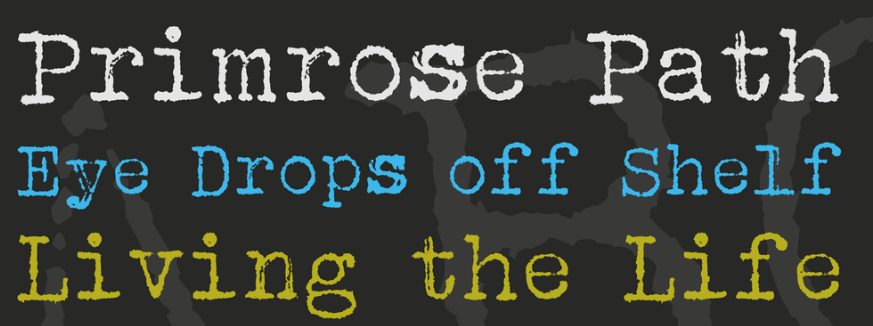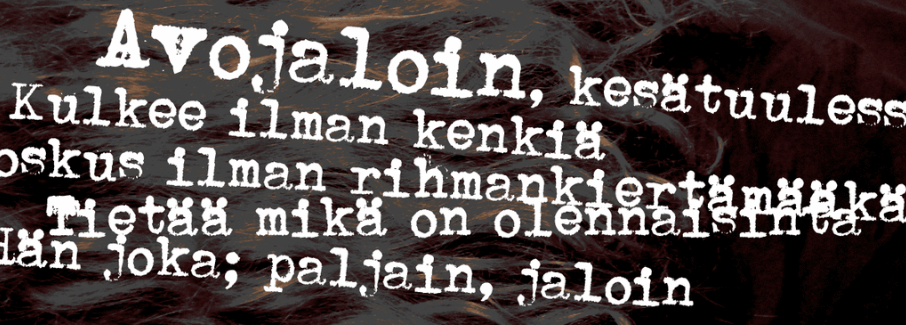
12 лучших шрифтов для пишущей машинки для классического стиля писателя
Опубликовано: 2018-10-27В наши дни кажется, что все соревнуются, чтобы создать самый современный дизайн. Тем не менее, есть что сказать о том, чтобы время от времени погружаться в ностальгию. В некоторых случаях классический шрифт пишущей машинки может быть идеальным элементом, чтобы добавить немного винтажного стиля в ваш дизайн.
В этой статье мы собираемся показать вам 12 наших любимых шрифтов для пишущей машинки. Пойдем винтаж!
12 лучших шрифтов для пишущей машинки для классического образа писателя
В этом обзоре мы сосредоточились на забавных шрифтах для пишущей машинки, которые легко читать. Таким образом, вы сможете использовать их как часть любого элемента вашего дизайна, хотя они особенно хорошо подходят для логотипов.
1. Пишущая машинка почтовых марок
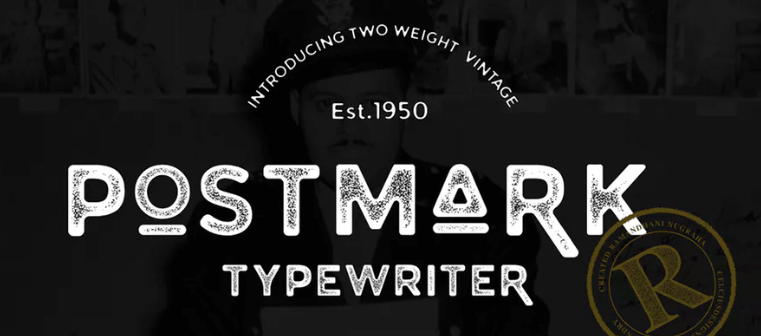
Для начала у нас есть Postmark Typewriter, прочный шрифт, который выглядит так, будто его выплюнули из самой старой пишущей машинки, которую вы можете найти. Этот шрифт без засечек имеет толстые линии (что облегчает чтение) и не будет выглядеть неуместным на современном сайте, несмотря на его наследие.
2. Семейство шрифтов Manson
Далее, семейство шрифтов Manson выглядит так, как будто оно появилось прямо на пишущей машинке 3018. Этот шрифт с засечками включает три разных веса, самый легкий из которых будет отлично смотреться на веб-сайтах, связанных с технологиями. Кроме того, по мере того, как шрифт становится толще, он становится более причудливым, что делает его универсальным вариантом.
3. Не мой тип
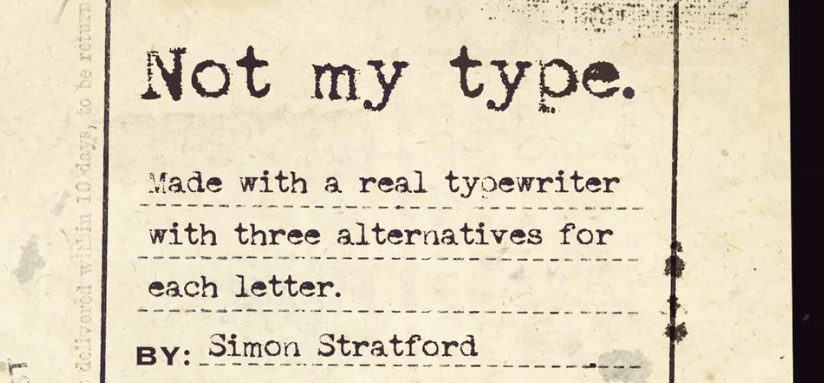
Not My Type - это шрифт, который вы ожидаете увидеть на старых открытках времен Второй мировой войны. У него выцветшие границы, и есть заметная разница между толщиной стеблей и штрихов. На практике это сочетание дает почти рукописный стиль, только более механический.
4. Заговор
Сторонники заговора часто бывают немного «чокнутыми», и этот шрифт прекрасно отражает их причудливость. Хотя похоже, что это написано на пишущей машинке, вы можете заметить, что буквы не идеально выровнены, что придает шрифту более беззаботный стиль. Мы бы не рекомендовали использовать его на бизнес-сайте, но он не будет выглядеть неуместным в блоге или портфолио.
5. Секретная пишущая машинка
Secret Typewriter - отличное название шрифта и идеальное описание стиля этого шрифта. Хотя этот шрифт очень легко читать, вы заметите, что большая часть его букв покрыта кистью, из-за чего он выглядит нечетким. Эти недостатки - идеальный способ добавить немного стиля к простому, элегантному шрифту, который отлично подходит для блогов.
6. Типы старых газет
Old Newspaper Types находится на грани между пишущей машинкой и готическим шрифтом. Его волнистые линии станут отличным дополнением, если вы хотите добавить немного причуды своему сайту. Однако из-за его уникального стиля мы рекомендуем использовать его только для заголовков, поскольку он плохо переносится на меньшие размеры.
7. Плохо штампованные
Если вы когда-нибудь хотели использовать шрифт, который выглядит как буквы из записки о выкупе, одобренной ТВ, Badly Stamped поможет вам. Это определенно не тот шрифт, который вы хотите использовать для контента или подзаголовков вашего сайта, но он является отличным вариантом для логотипов или для раздела заголовка.
8. Молотковые ключи.
Из всех шрифтов, которые мы видели до сих пор, Hammer Keys - это тот, который ближе всего передает стиль старой пишущей машинки. Стиль шрифта тонкий и почти хрупкий, что не делает его хорошим вариантом для мелкого текста. Однако, несмотря на это, Hammer Keys - это то, что вам нужно, если вы ищете почти точную копию стиля винтажной пишущей машинки.
9. Ремингтон Ривьера
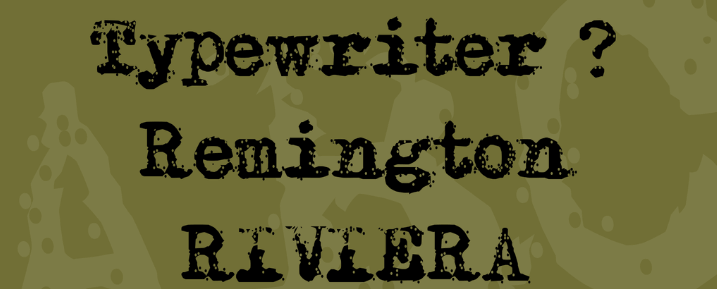
Если вы знаете свои пишущие машинки, вы узнаете название Remington Riviera. Remington Riviera - это не только стильный шрифт, но и название популярной модели пишущей машинки. Ривьера выделялась толстыми буквами, которые она производила, и этот шрифт повторяет стиль. Кроме того, он даже добавляет несколько пятен для завершения эффекта, и это отличный вариант для логотипа блога.
10. Traveling_Typewriter.
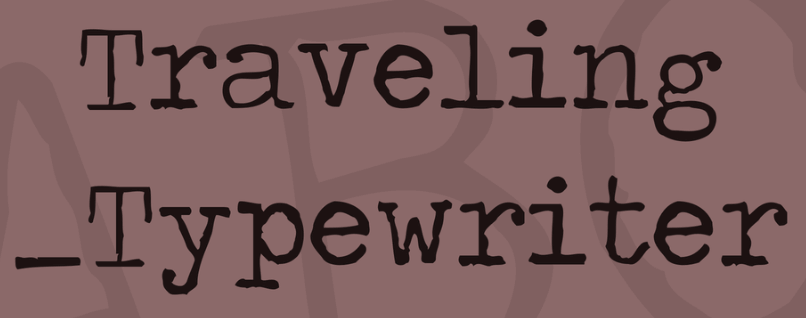
Чтобы продолжить тренд шрифтов на основе реальных моделей пишущих машинок, у нас есть Traveling_Typewriter. Этот конкретный шрифт был смоделирован в стиле пишущей машинки Olympia Traveler de Lux. Как следует из названия, Olympia была несколько легче и компактнее, чем другие пишущие машинки той эпохи, хотя мы до сих пор не можем себе представить, чтобы кто-то таскал ее с собой.
Когда дело доходит до стиля, Traveling_Typewriter также делает вещи легкими. У этого шрифта тонкие ножки, а дизайн немного шаткий. Тем не менее, он отлично выглядит и читается даже при небольшом размере, поэтому вы все равно можете использовать его для контента своего блога.
В большинстве случаев мы рекомендуем шрифты для пишущей машинки для дизайна блогов и личных сайтов. Например, пишущая машинка для почтовых марок будет отлично смотреться на прочном туристическом веб-сайте. С другой стороны, семейство шрифтов Manson достаточно современно, и вы можете использовать его в логотипе.